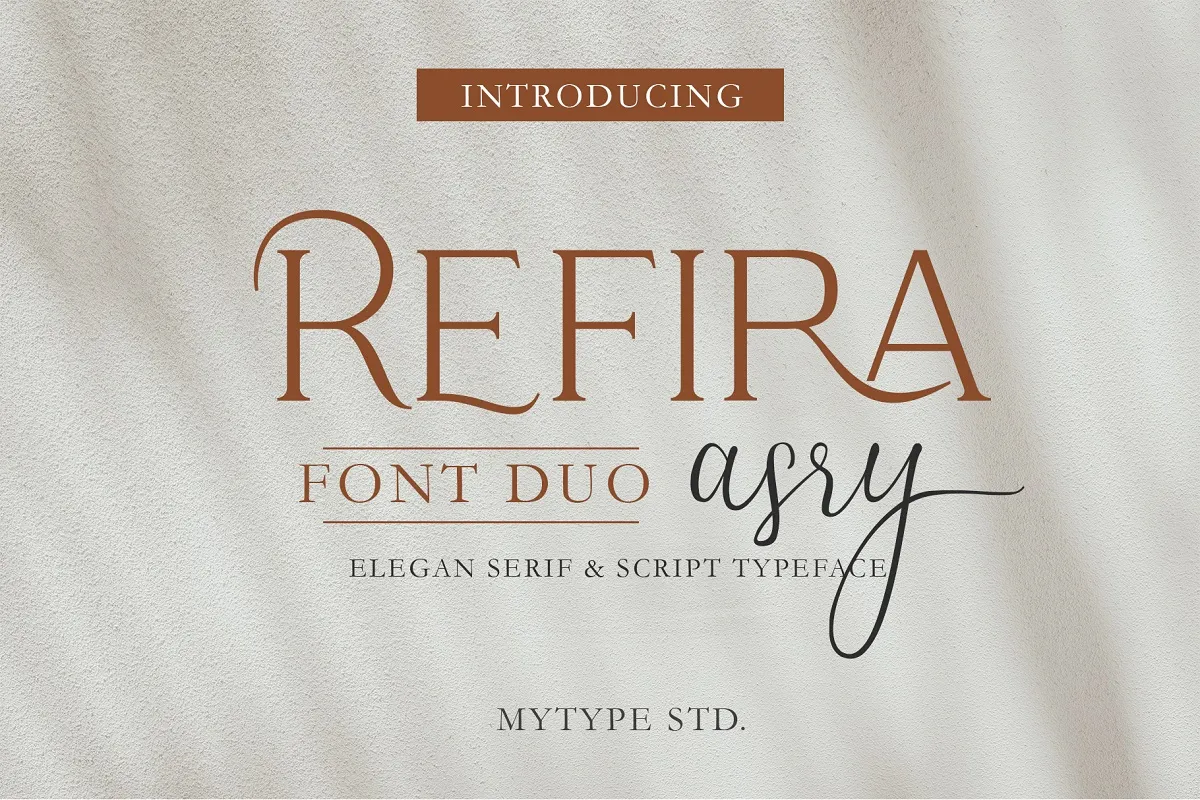
Refira Asry Font – Download Grátis
A Refira Asry é uma paixante perfeita para aqueles que buscam um equilíbrio elegante entre elegância tradicional e modernidade contemporânea. Esta dupla de tipos, um cursive e outro serif, foi criada pelo designer Icreatype para contrastar e complementar-se com sofisticação e bom gosto. O refira Asry Serif oferece linhas sólidas e robustas que ressaltam a complexidade das letras do tipo script. Suas características são ideais para o uso em materiais de publicação, design editorial ou até mesmo para criar um design gráfico com uma estética sofisticada. O seu desenho elegante é adaptado ao moderno padrão de design, mantendo sempre a essência e a beleza tradicionais dos tipos serifos. Junto com o refira Asry Script, você terá duas opções para incorporar um toque distintivo em suas criações. O script oferece fluidos e sofisticados traços que permitem criar uma conexão visual elegante entre os elementos do design. Esse conjunto de tipos é perfeito tanto para projetos profissionais quanto para aqueles que buscam uma fonte única e moderna no seu trabalho gráfico, sendo a Refira Asry uma ótima opção para quem procura um tipo versátil para combinar com diferentes estilos e materiais.